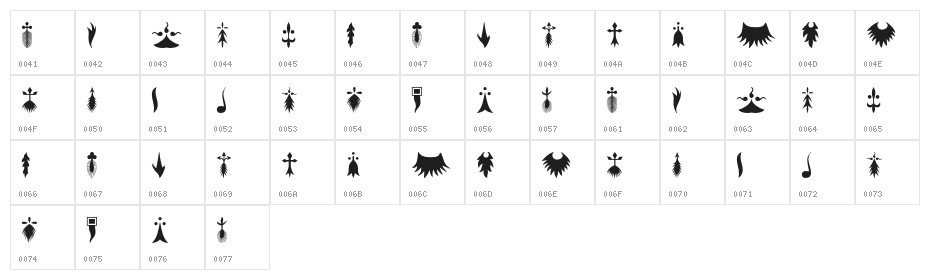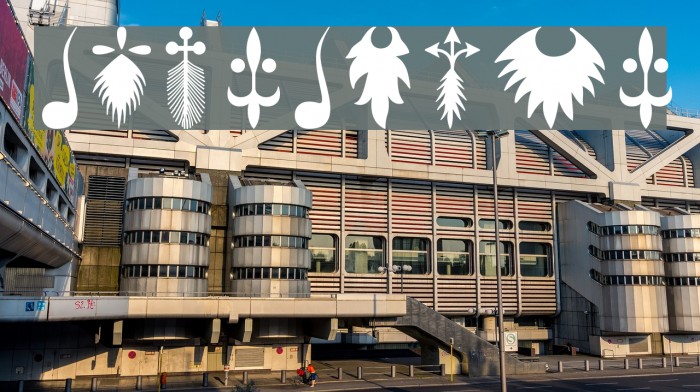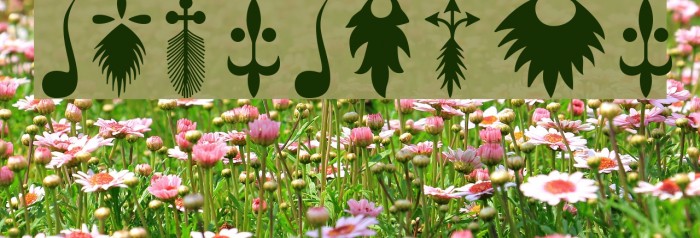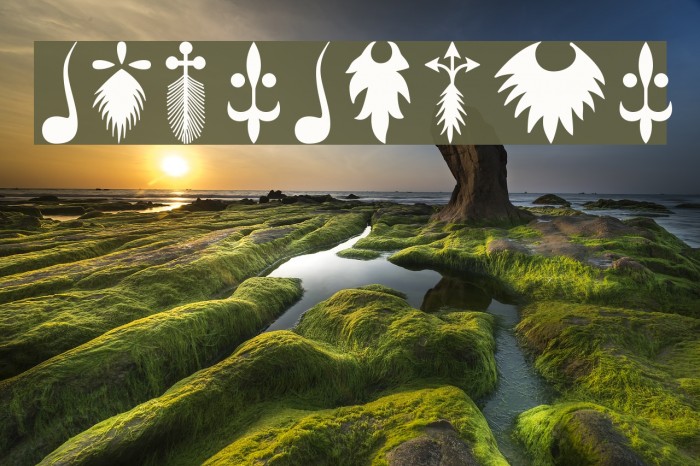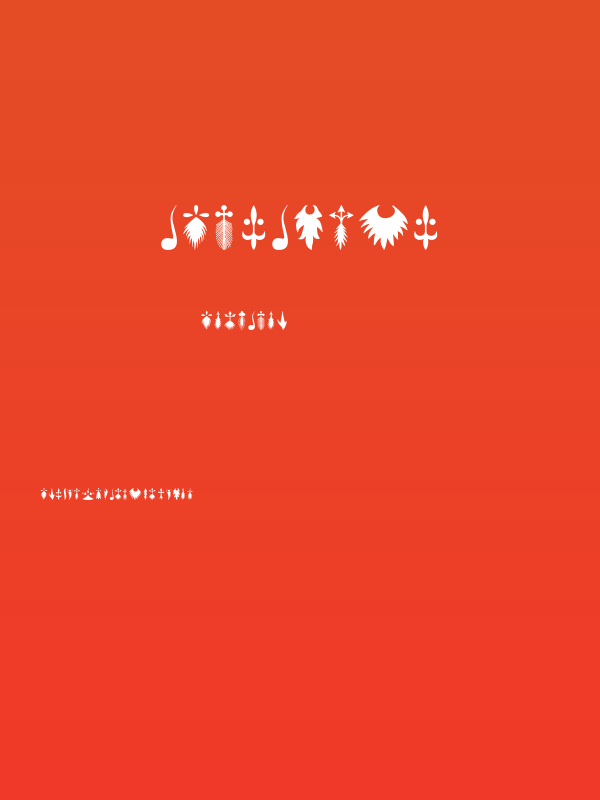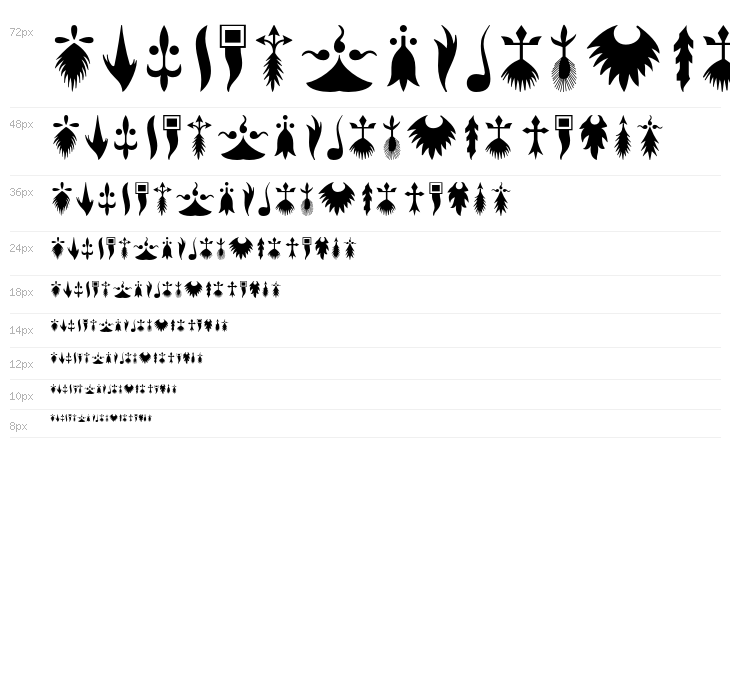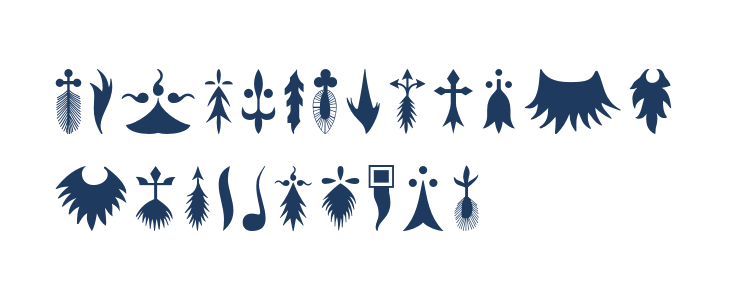
RTA Ermine Font
| Caz de utilizare | Logos, Decorative elements |
| Proiecte propuse | These symbols could be used in artistic projects, such as logo design, pattern creation, or as decorative elements in graphic design. |